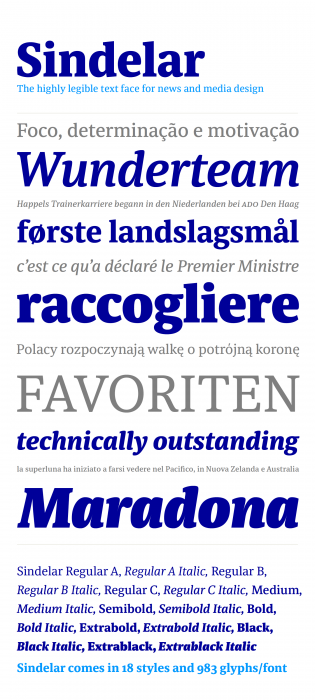
Sindelar – Eine Textschrift für Zeitungen und Magazine
Ich freue mich, hiermit bekannt geben zu können, dass die Schriftfamilie Sindelar nach mehrjähriger, intensiver Entwicklungszeit veröffentlicht und ab sofort erhältlich ist. Sindelar ist eine Textschrift, die sich hervorragend für die Verwendung in Zeitungen und Magazinen eignet. Sie verfügt über 18 Schnitte, wurde zwischen 2009 und 2014 entwickelt und ist in ihrem Einsatz ideal mit meiner ersten Schriftfamilie Acorde kombinierbar. Sindelar ist bei Willerstorfer Font Foundry erschienen und hier zu erwerben: www.willerstorfer.com
Über die Schriftfamilie Sindelar
Sindelar ist eine leistungsfähige, zeitgemäße Textschrift, die den hohen Anforderungen des modernen Zeitungs- und Mediendesigns gewachsen ist. Ihre große x-Höhe, ihr geringer Kontrast und ihre robusten Serifen garantieren eine hervorragende Lesbarkeit in kleinen Größen. Die ausgewogenen, mit Bedacht gewählten Proportionen machen die Schrift ökonomisch (platzsparend), ohne sie zu schmal erscheinen zu lassen. Diese Charakteristika machen die Schrift zu einer idealen Wahl für den umfangreichen Einsatz in Zeitungen und Magazinen – sowohl am Papier als auch am Screen (Webfonts in Bälde verfügbar).
Sindelar, benannt nach dem österreichischen Fußballspieler Matthias Sindelar (1903–1939), einem der besten Spieler seiner Zeit, hat mit dem Fußballer zwei wesentliche Kriterien gemein: ihre technische Finesse und ihre Art und Weise, bis ins kleinste Detail ästhetisch zu agieren. Der Spitzname des Fußballers, »Der Papierene«, verweist wiederum elegant auf das Medium.
Obwohl die Schrift für kleine Größen optimiert wurde, geben der geringe Kontrast und die robusten Serifen der Schrift in großen Größen einen starken Ausdruck und eine unverwechselbare Erscheinung. Die kalligraphischen Einflüsse können in den Italic-Schnitten am besten wahrgenommen werden. Die kursiven Buchstaben sind entsprechend ihrer Formen und Proportionen in leicht unterschiedlichen Winkeln geneigt und resultieren im Verband in einem ausgewogenen und doch lebendigen Schriftbild. Sindelar ist in 18 Schnitten verfügbar – jeweils neun Schnitte in Roman und Italic. Jeder Schnitt verfügt über einen Zeichensatz von mehr als 980 Glyphen und über zahlreiche OpenType Features.
Das umfangreiche Specimen-PDF gibt einen exzellenten Überblick über die Schriftfamilie Sindelar. Es zeigt zahlreiche Beispiele aller Schnitte, den kompletten Zeichensatz und informiert über alle unterstützten OpenType Features.
Vielen Dank für Deine Schriftvorstellung – mir als Anwenderin gefällt Deine Schrift auf den ersten Blick sehr gut! Nach einem Blick auf die Glyphentabelle sei mir die Frage erlaubt, ob Du irgendwo noch ein Versal-Eszett versteckt hast (oder habe ich es übersehen?)? Das Versal-Eszett liegt vielen von uns hier im Forum am Herzen und wäre für mich zum Beispiel ein echtes Kaufargument. Falls Du keines in die Sindelar integriert hast – könntest Du Dir vorstellen, noch eines zu ergänzen?  :-D
Schick. Auch wenn ich das Versal-Eszett ähnlich wie Kathrin noch vermisse, darfst Du Dich gern so frei fühlen die Schrift auch in unserem Wiki zu präsentieren. Dann kann man sie auch in entsprechende Listen aufnehmen und sie geht nicht wieder so schnell unter.
Was ich etwas schade finde, ist, dass die Strichstärken-Extreme bei den üppigen neun Gewichten nicht deutlicher ausfallen. Statt der drei recht ähnlichen Regular-Versionen würde mich etwas Leichtes (Light, Thin, Hair) womöglich mehr zu Kauf reizen.
Nichtsdestotrotz macht die Gestaltung einen ziemlich hochwertigen Eindruck auf mich und der Zeichenumfang ist toll. :-)  :bow: